Top 10 font chữ miễn phí đẹp nhất trên Canva
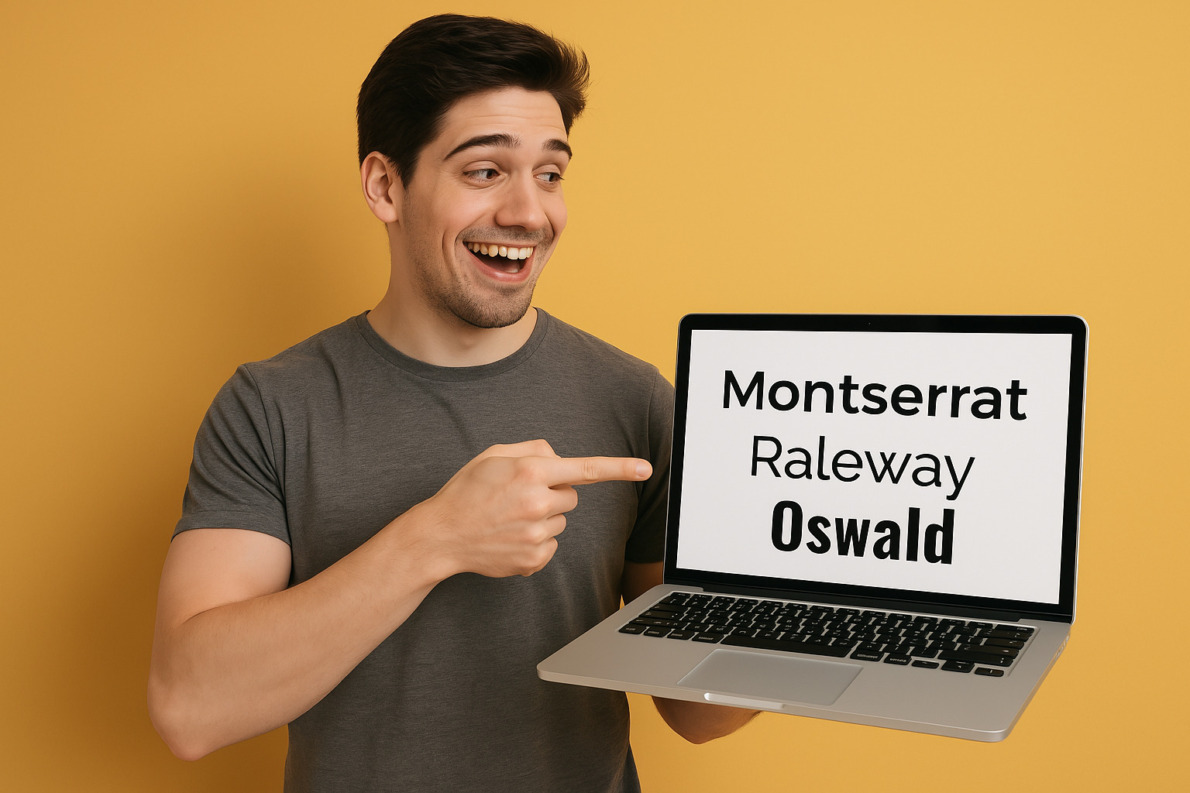
Font chữ là một yếu tố quan trọng trong thiết kế, giúp truyền tải thông điệp một cách hiệu quả và tạo dấu ấn riêng cho thương hiệu. Nếu bạn đang sử dụng Canva để thiết kế, chắc hẳn bạn sẽ muốn biết những font chữ miễn phí đẹp nhất để áp dụng cho các dự án của mình. Dưới đây là top 10 font chữ miễn phí trên Canva mà bạn không thể bỏ qua!
1. Montserrat – Hiện đại và chuyên nghiệp
Montserrat là một trong những font chữ sans-serif phổ biến nhất trên Canva. Với kiểu chữ gọn gàng, hiện đại và dễ đọc, Montserrat rất phù hợp cho các thiết kế thương hiệu, tiêu đề website và bài đăng trên mạng xã hội.
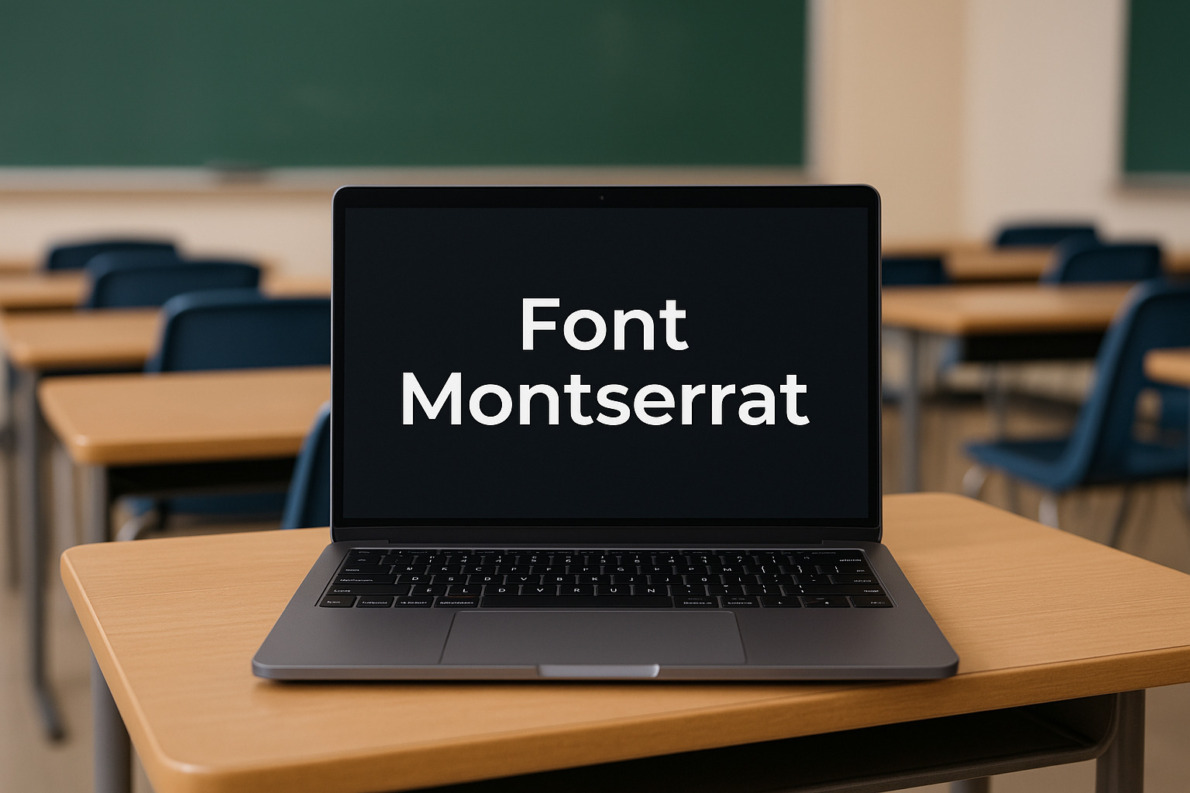
2. Lora – Thanh lịch và dễ đọc
Lora là một font serif mang phong cách thanh lịch, nhẹ nhàng nhưng vẫn giữ được sự chuyên nghiệp. Nó rất phù hợp cho các bài viết blog, thiết kế sách và nội dung mang tính nghệ thuật.
3. Raleway – Độc đáo và tinh tế
Raleway có các nét chữ mảnh, tinh tế, tạo cảm giác hiện đại nhưng vẫn có chút cổ điển. Font này phù hợp cho các tiêu đề lớn, logo và nội dung sáng tạo.
4. Oswald – Mạnh mẽ và thu hút
Oswald là một font sans-serif đậm, lý tưởng cho các tiêu đề lớn và thiết kế poster. Nó giúp nội dung nổi bật và thu hút sự chú ý ngay lập tức.
5. Poppins – Đơn giản và linh hoạt
Poppins là một font chữ hình học với các đường nét tròn trịa, dễ đọc và phù hợp với nhiều loại thiết kế khác nhau như website, danh thiếp, slide thuyết trình.
6. Playfair Display – Cổ điển và sang trọng
Playfair Display mang phong cách serif cổ điển, thường được sử dụng trong các thiết kế thời trang, blog cá nhân hoặc những dự án cần sự sang trọng, đẳng cấp.
7. Open Sans – Đa dụng và dễ đọc
Open Sans là một font chữ không chân có thiết kế tối giản, dễ đọc trên cả màn hình và bản in. Nó rất phù hợp với các thiết kế website, blog và tài liệu chuyên nghiệp.
8. Dancing Script – Mềm mại và nghệ thuật
Nếu bạn đang tìm một font chữ viết tay đẹp trên Canva, Dancing Script là lựa chọn hoàn hảo. Font này mang đến cảm giác nghệ thuật và phù hợp với các thiết kế thiệp mời, tiêu đề sáng tạo.
9. Pacifico – Thân thiện và vui nhộn
Pacifico là một font chữ viết tay có phong cách vui nhộn, gần gũi. Nó thường được sử dụng cho các thiết kế liên quan đến trẻ em, thực phẩm hoặc các dự án sáng tạo.
10. Merriweather – Truyền thống và dễ đọc
Merriweather là một font serif có thiết kế truyền thống nhưng không lỗi thời. Font này thường được sử dụng trong các bài viết dài, sách hoặc website có nhiều nội dung chữ.
Kết luận
Canva cung cấp rất nhiều font chữ miễn phí đẹp và chuyên nghiệp, giúp bạn dễ dàng sáng tạo các thiết kế ấn tượng. Hy vọng danh sách này sẽ giúp bạn lựa chọn được font chữ phù hợp cho dự án của mình. Hãy thử ngay trên Canva và tận dụng những font chữ này để tạo ra những thiết kế tuyệt vời nhé!